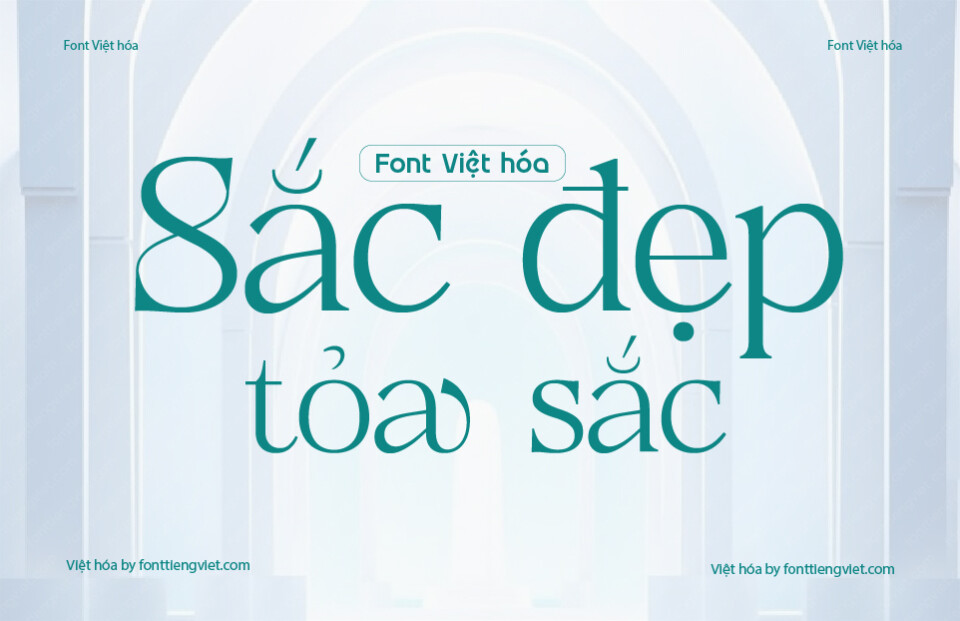
Font Việt hóa 1FTV VIP Metrolin
Font Việt hóa 1FTV VIP Metrolin – Bộ Font Chữ Đẳng Cấp Cho Thiết Kế Hiện Đại
Giới thiệu về Font Việt hóa 1FTV VIP Metrolin trong thiết kế đồ họa
Trong thế giới sáng tạo ngày nay, việc lựa chọn một bộ Font Miễn Phí chất lượng luôn là ưu tiên hàng đầu của các nhà thiết kế. Font Việt hóa 1FTV VIP Metrolin nổi lên như một giải pháp hoàn hảo cho những ai đang tìm kiếm sự kết hợp giữa nét hiện đại và tính ứng dụng cao. Đây là bộ phông chữ được tinh chỉnh kỹ lưỡng, hỗ trợ đầy đủ bộ gõ tiếng Việt với các dấu thanh được đặt chuẩn xác, giúp người dùng không còn lo lắng về lỗi hiển thị khi soạn thảo văn bản hay thiết kế ấn phẩm truyền thông. Với đường nét sắc sảo và bố cục cân đối, bộ font này mang đến một luồng gió mới cho các dự án sáng tạo từ đơn giản đến phức tạp.
Đặc điểm nổi bật của Font Việt hóa 1FTV VIP Metrolin
Thiết kế hình học tinh tế và sang trọng
Font Việt hóa 1FTV VIP Metrolin được xây dựng dựa trên cấu trúc hình học (geometric) hiện đại, lấy cảm hứng từ các dòng chữ in ấn của thế kỷ 20 nhưng được cải biên để phù hợp với thẩm mỹ đương đại. Các nét chữ có độ dày vừa phải, tạo cảm giác thanh thoát nhưng vẫn giữ được sự chắc chắn cần thiết. Điều này giúp bộ font không chỉ đẹp về mặt thị giác mà còn cực kỳ dễ đọc trên cả màn hình kỹ thuật số lẫn bản in vật lý. Sự đồng nhất trong từng ký tự giúp cho tổng thể thiết kế trở nên chuyên nghiệp và bắt mắt hơn bao giờ hết.
Khả năng ứng dụng đa dạng trong nhiều lĩnh vực
Nhờ vào tính linh hoạt tuyệt vời, Font Việt hóa 1FTV VIP Metrolin thường xuyên được sử dụng trong thiết kế bộ nhận diện thương hiệu, logo, và bìa sách. Đối với các bạn học sinh và sinh viên, đây là công cụ đắc lực để trang trí bài thuyết trình hoặc làm báo tường thêm phần sinh động. Trong lĩnh vực marketing, bộ font này giúp các banner quảng cáo trở nên thu hút và dễ gây ấn tượng với khách hàng ngay từ cái nhìn đầu tiên. Bạn có thể dễ dàng kết hợp nó với các kiểu chữ serif truyền thống để tạo nên sự tương phản thú vị cho tác phẩm của mình.
Cách tối ưu hóa Font Việt hóa 1FTV VIP Metrolin cho website
Lợi ích khi sử dụng font chuẩn hóa tiếng Việt
Sử dụng Font Việt hóa 1FTV VIP Metrolin giúp website của bạn tránh được tình trạng nhảy font hoặc mất dấu thường gặp ở các bộ phông quốc tế chưa được việt hóa. Một phông chữ đẹp không chỉ cải thiện trải nghiệm người dùng mà còn góp phần nâng cao điểm số SEO cho trang web nhờ vào sự chuyên nghiệp trong trình bày văn bản. Khi nội dung được hiển thị rõ ràng, người đọc sẽ ở lại trang lâu hơn, từ đó tăng tỷ lệ chuyển đổi hiệu quả. Đây là yếu tố then chốt để xây dựng uy tín cho các dự án trực tuyến hiện nay.
Kết luận về bộ phông chữ 1FTV VIP Metrolin
Tổng kết lại, đây là một trong những bộ phông chữ đáng sở hữu nhất hiện nay dành cho cộng đồng thiết kế Việt Nam. Sự chỉn chu trong từng nét vẽ cùng khả năng hỗ trợ tiếng Việt hoàn hảo đã khẳng định giá trị của nó trong lòng người dùng. Nếu bạn đang tìm kiếm một công cụ để nâng tầm sản phẩm sáng tạo của mình, đừng ngần ngại trải nghiệm ngay Font Miễn Phí, Font Việt Hóa, Font Việt hóa 1FTV VIP Metrolin để thấy được sự khác biệt vượt trội mà nó mang lại cho mỗi dự án của bạn.